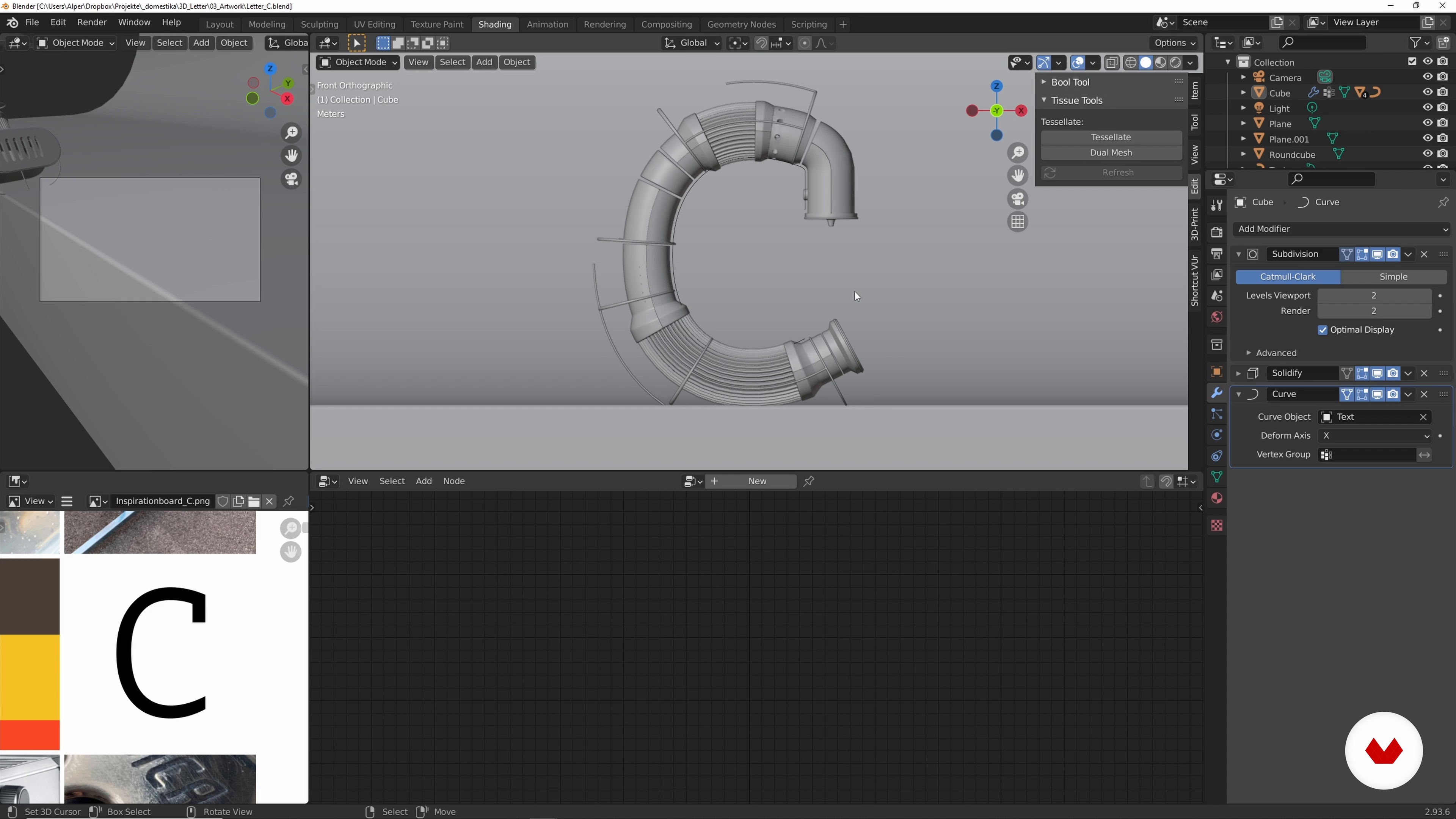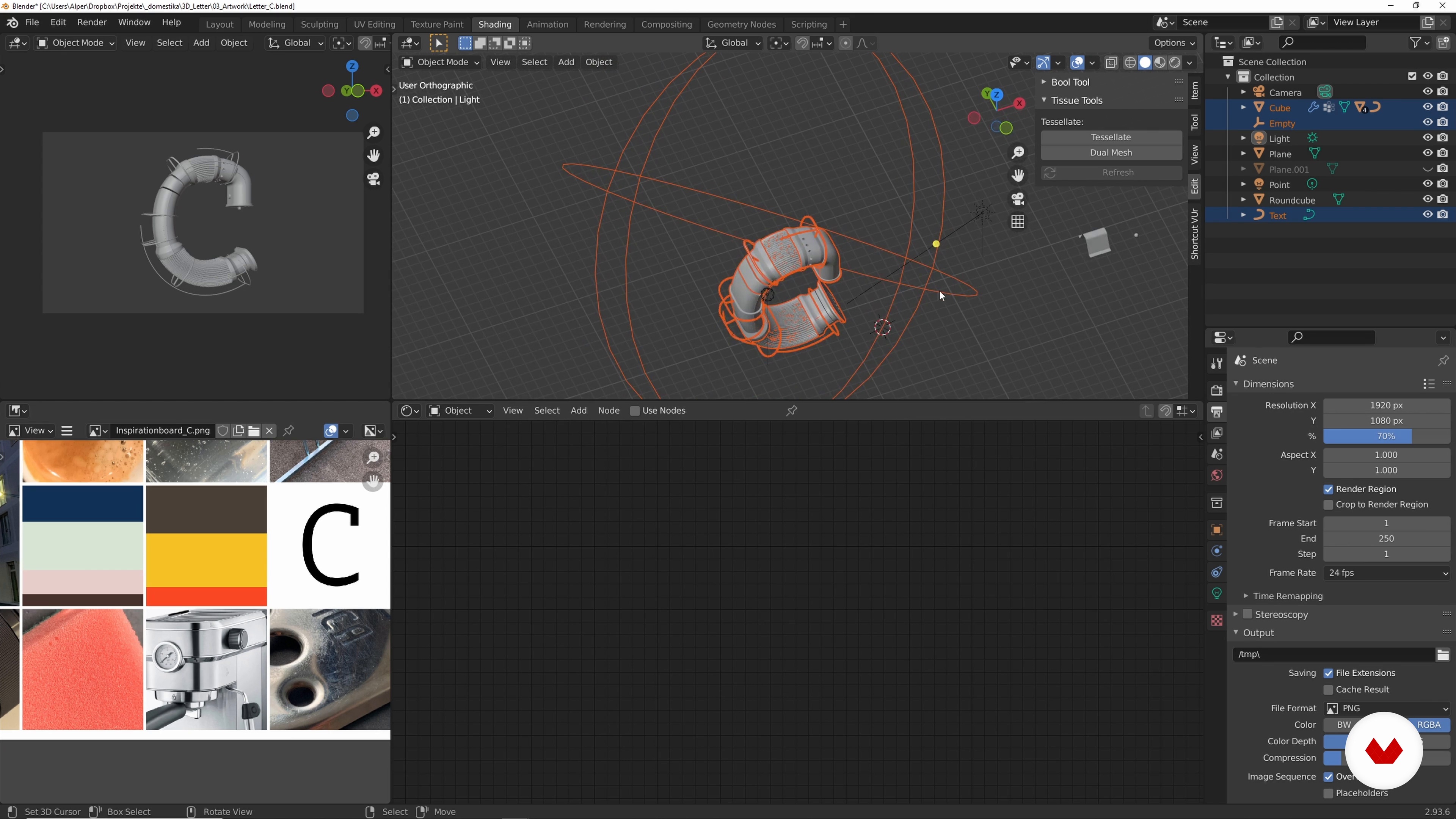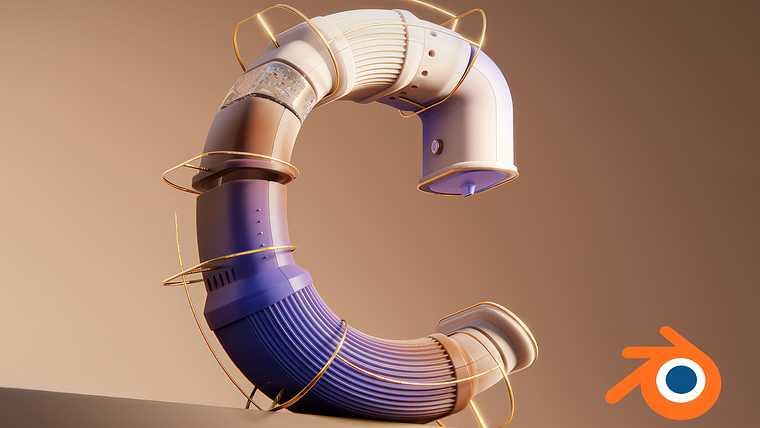
Objetos e materiais da vida cotidiana que se comportam de uma forma diferente: estes são os protagonistas das obras de Alper Dostal. O designer e artista 3D gosta de tirar certos elementos do contexto, como letras, modelando composições interessantes a partir delas. Além disso, ele explora o contraste do industrial com o orgânico em suas obras, entre outros.
Neste curso online, você aprenderá a criar letras repletas de estilo e capazes de contar uma história. Alper ensinará como desenvolver seu projeto de tipografia, da busca por inspiração até a escolha das cores. Você fará suas letras com estruturas modulares no Blender e descobrirá como desenvolver texturas, combinar materiais e cores para obter uma composição elegante.
Para começar, você conhecerá Alper Dostal, seu professor neste curso. Ele contará sobre sua profissão anterior e como acabou se especializando em design 3D. Também compartilhará as influências que moldaram seu estilo.
Com a ajuda de Alper, você aprenderá a preparar seu design e encontrar inspiração para gerar novas ideias. Para isso, você buscará referências, materiais, formas, texturas e cores, pensará em um tema para suas letras e combinará tudo em um mood board, que será o ponto de partida do seu projeto.
Já na terceira unidade, seu professor ensinará como configurar o Blender e como otimizar seu trabalho com o programa. Você aprenderá a modelar as formas básicas e aplicará curvas para transformá-las em letras. Depois, você verá como combinar as cores e elaborar os materiais a partir de diversas texturas.
Em seguida, você vai trabalhar com a composição e iluminação de suas letras. Alper explicará como encontrar a melhor posição da câmera e como usar diferentes fontes de luz, cores e intensidades para obter uma iluminação interessante.
Por fim, você aplicará vários efeitos para conseguir um resultado realista e otimizará a imagem antes de renderizá-la. Após editá-la e adicionar os últimos detalhes no Photoshop, você descobrirá as vantagens de trabalhar por seções ao modelar seus projetos.
Modelarás letras en 3D compuestas por diferentes secciones; combinarás colores, materiales y texturas; las colocarás en una escena con una buena iluminación y editarás tu diseño en Photoshop.
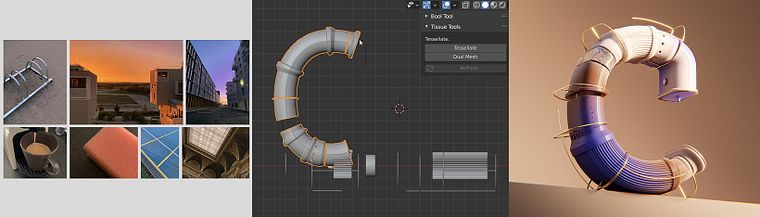
Você vai aprender a criar suas próprias artes 3D, montar paletas de cores, usar moodboards, modelar letras modulares e criar visualizações para redes sociais — incluindo iluminação, materiais, renderização e pós-produção.
Você vai aprender a coletar inspiração do dia a dia, plataformas online (Pinterest, Google), fotografia e moodboards, organizando tudo de forma sistemática para seus projetos.